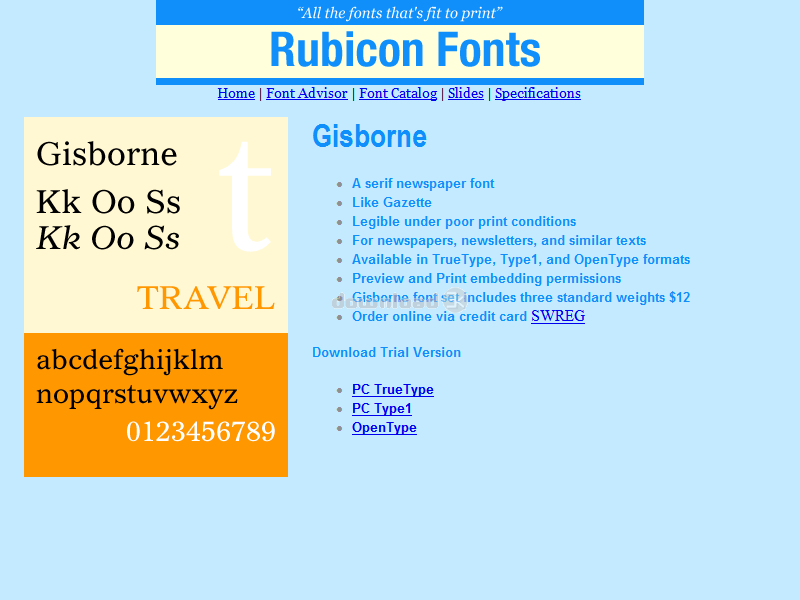
"Serif газеты шрифт, привет разрешения, намекнул, kerned."
Serif газеты шрифт с массовый призыв. Как Gazette. Разборчивы в условиях плохой печати. Для газеты, информационные бюллетени и другие подобные тексты. Рекомендуемый размер 8,5 балла. Точная и намекнул, соответствующий шрифт метрик, стандартный набор символов, кернинг пар. Профессиональное качество печати на струйных, лазерных, наборщик до 3500 точек на дюйм. Покупатели получают 3 варианта шрифта следующим образом: Roman, курсив, полужирный.Требования: No special requirements.